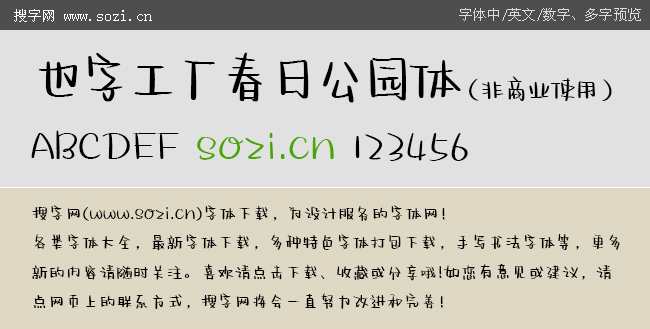
也字工廠春日公園體
搜字網(wǎng)給大家提供一款也字工廠春日公園體(非商業(yè)使用)中文字體下載,也字工廠春日公園體是一款手寫風(fēng)格的卡通字體,字體書寫流暢自然,字形充滿趣味。具有很好的視覺效果。適合應(yīng)用于藝術(shù)設(shè)計(jì)、平面宣傳設(shè)計(jì)、網(wǎng)頁設(shè)計(jì)、海報(bào)設(shè)計(jì)等應(yīng)用(此字體為個(gè)人非商用版,商用可以聯(lián)系:官方網(wǎng)址:https://yefont.com/home,聯(lián)系方式:13798980448)。